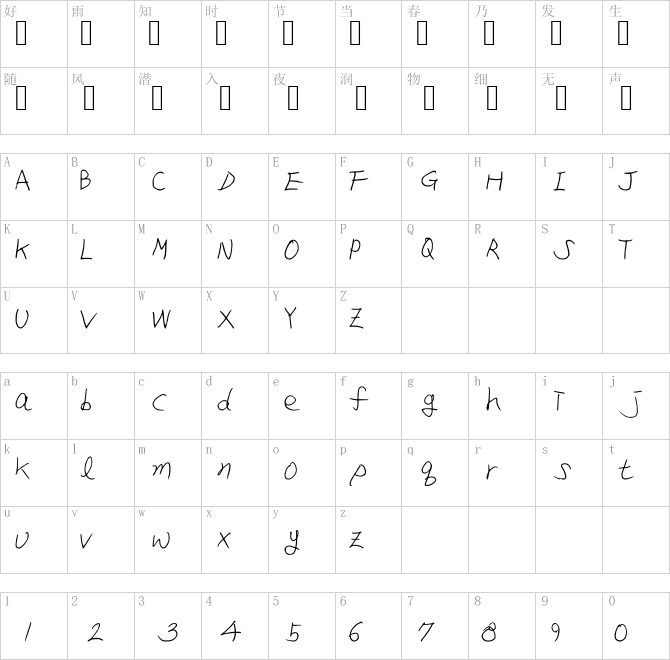
나눔손글씨 소방관의 기도韩国字体
나눔손글씨 소방관의 기도韩国字体,这款字体结构工整、笔画清晰,兼顾美观与易读性,适用于标题、正文、海报、包装、LOGO 等多种场景。字形优雅稳定,风格百搭耐看,适配日常排版与创意设计,让文字呈现更舒适、更具质感。나눔손글씨 소방관의 기도韩国字体一笔一画,皆是细节,以均衡的比例、流畅的线条打造舒适视觉体验,字形端正大气,风格简约现代。无论是商业设计、品牌宣传还是日常排版,都能轻松驾驭,让文字更有格调与力量。나눔손글씨 소방관의 기도韩国字体字体下载。
• 字体名称:나눔손글씨 소방관의 기도
• 字体风格:Regular
• 字体标识:CLOVA OCR : Nanum SoBangGwanEuiGiDo
• 字体全称:나눔손글씨 소방관의 기도
• PostScript:NanumSoBangGwanEuiGiDo